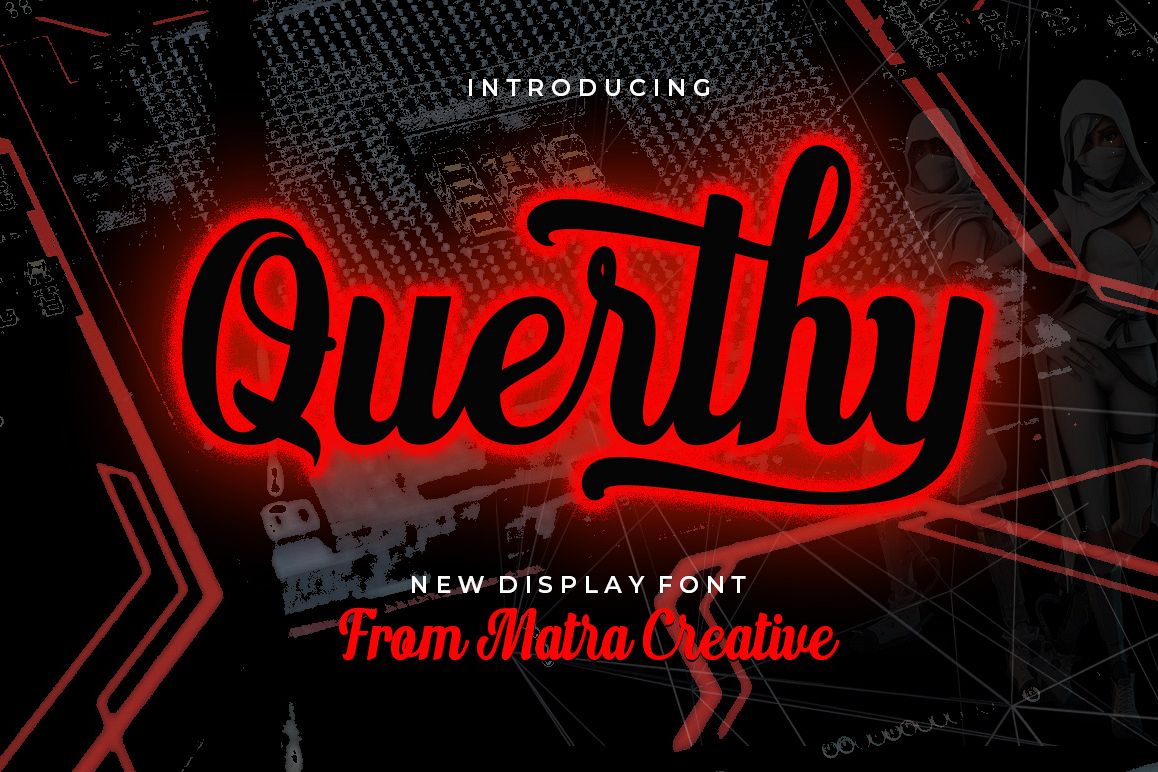
Querthy Script
Querthy - Font Tulisan Tangan adalah font skrip kuasjak bahasa tulisan tangan asli, memungkinkan Anda mengubah jenis menjadi karya yang menarik dan indah. Tampilan tulisan tangan menambahkan sentuhan manusia pada berbagai hal dan dilengkapi dengan banyak detail yang penuh cinta.
Querthy- Font Tulisan Tangan memiliki banyak alternatif yang memungkinkan Anda untuk membuat teks Anda yang sangat mirip dengan tulisan tangan dengan semua ketidaksempurnaan dan bagian-bagian yang dapat menulis tulisan tangan yang nyata. Querthy akan bekerja dengan sempurna untuk fashion, merek e-commerce, blog tren, butik pernikahan, atau apa pun yang ingin tampil mewah dan chic.
Fitur:
1. Huruf Besar & Huruf Kecil
2. Alternatif Stylistic
3. Standart Ligatures
4. Numerals & Punctuations (OpenType Standard)
5. Aksen (Karakter bermutu)
6. PUA Dikodekan